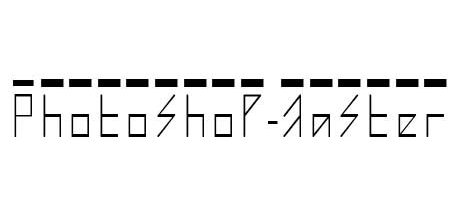
Ну шрифт прикольный!! :)) Я таких еще не встречал!
Совет. Чтобы отобразить первый символ индекса (две верхних горизонтальных линии), нужно нажать в английской раскладке апостроф (клавиша Ё в левом верхнем углу).
Спасибо. Удобно почтовые индексы на конверты вписывать ;)
ахахах..какая странная М
Темный шрифт. Спасибо!
нет, не пишет
А он по русски пишет??